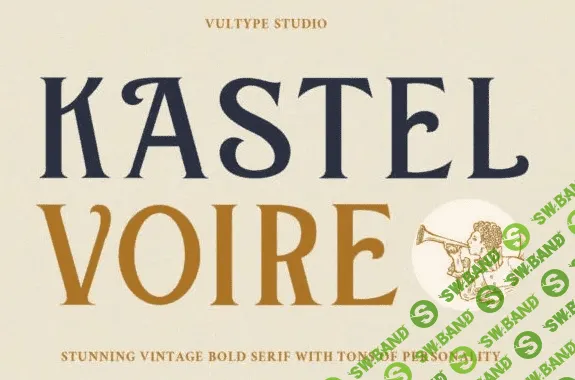
Kastel Voire - это классический шрифт дисплея.
Минимальный контрастный вид, который был синонимом моды на протяжении десятилетий. Этот шрифт одновременно современный и ностальгический, отлично подходит для логотипов, мачт и тянущих цитат. Он прекрасно сочетается с минимальным безсерийным или легким шрифтом.